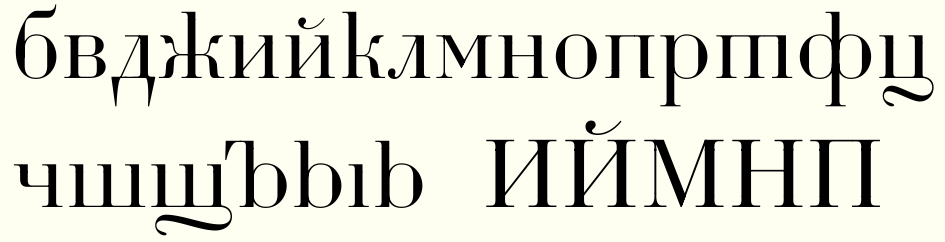
Шрифт Цицеро/DXCicero
В работе шрифт DXCicero. Цифровая версия по мотивам "Гарнитуры III/о Новикова" словолитни О.О.Гербек, русского текстового шрифта в стиле конца XVIII века. Планируется выпустить в двух начертаниях: светлое и более контрастное полужирное.